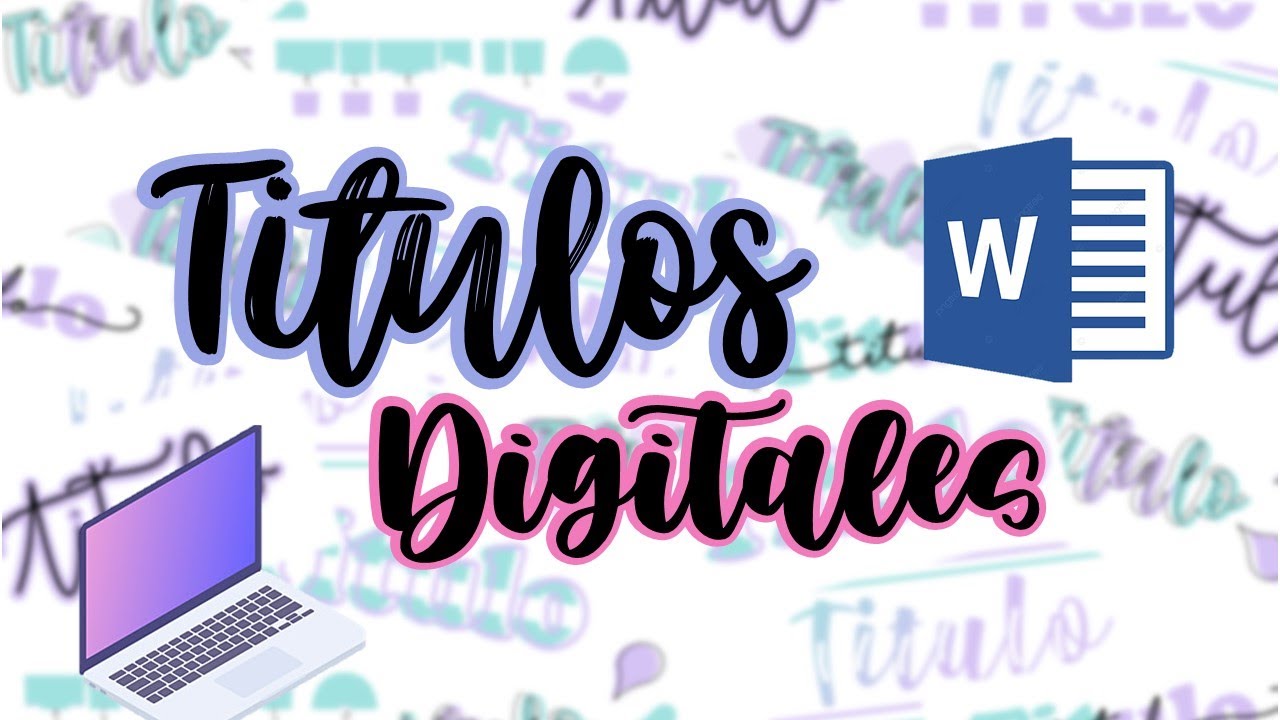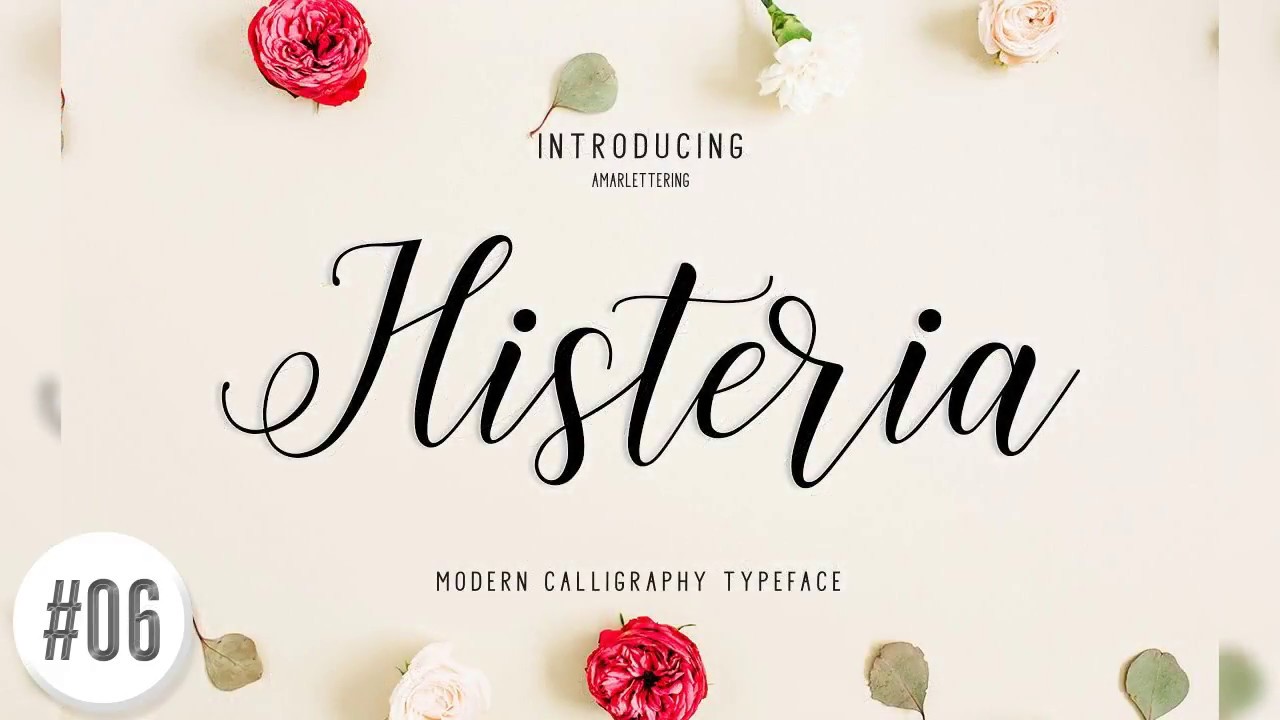
Tipografias Fuentes Bonitas Para Decorar En Word
Fuentes De Letras Mas Bonitas En Word Archives Tipografias Archivo de fuentes de descarga gratuita. búsqueda por orden alfabético, por estilo, por autor o por popularidad. En resumen, elegir una tipografía bonita para tus documentos en word puede mejorar su apariencia y hacer que destaquen. la clave está en encontrar un equilibrio entre el estilo y la legibilidad. ¡experimenta con diferentes tipos de letra y encuentra la combinación perfecta para cada ocasión!.
Descarga Hermosas Fuentes Para Tus Títulos En Word Tipografias Descargar 12005 letras bonitas fuentes. 1001 free fonts ofrece una gran selección de fuentes letras bonitas para windows, macintosh y linux. Una colección de diversas fuentes decorativas para uso personal y comercial. las mejores fuentes decorativas con ejemplos de escritura. Genera letras especiales para usar en word y google docs. caracteres unicode compatibles con microsoft word. gratis. Desde líneas limpias en negrita e itálica hasta divertidas curvas en 𝓬𝓾𝓻𝓼𝓲𝓿𝓪 y trazos dramáticos en 𝔊ó𝔱𝔦𝔠𝔬, obtienes más de 150 estilos listos para copiar y pegar en cualquier lugar.
Letras Bonitas Para Word Para Titulos Archives Tipografias Genera letras especiales para usar en word y google docs. caracteres unicode compatibles con microsoft word. gratis. Desde líneas limpias en negrita e itálica hasta divertidas curvas en 𝓬𝓾𝓻𝓼𝓲𝓿𝓪 y trazos dramáticos en 𝔊ó𝔱𝔦𝔠𝔬, obtienes más de 150 estilos listos para copiar y pegar en cualquier lugar. Con más de 2,256 fuentes word, desde sin serif hasta manuscritas, creemos que encontrarás la combinación perfecta para tus proyectos. ven y descrubre la tipografía que estabas buscando. Teniendo en cuenta estas recomendaciones y también escogiendo tu tipografía en función del tema, el público al que va dirigido tu texto y la extensión, podrás hacer un buen uso de las variadas posibilidades de fuentes que pone a tu disposición word office. Conoce las mejores tipografías para word y descárgalas gratis. te dejamos una lista de 30 tipos de letras para escribir en word. Todas las fuentes se pueden usar libremente para proyectos editoriales, educativos, comerciales y o personales.